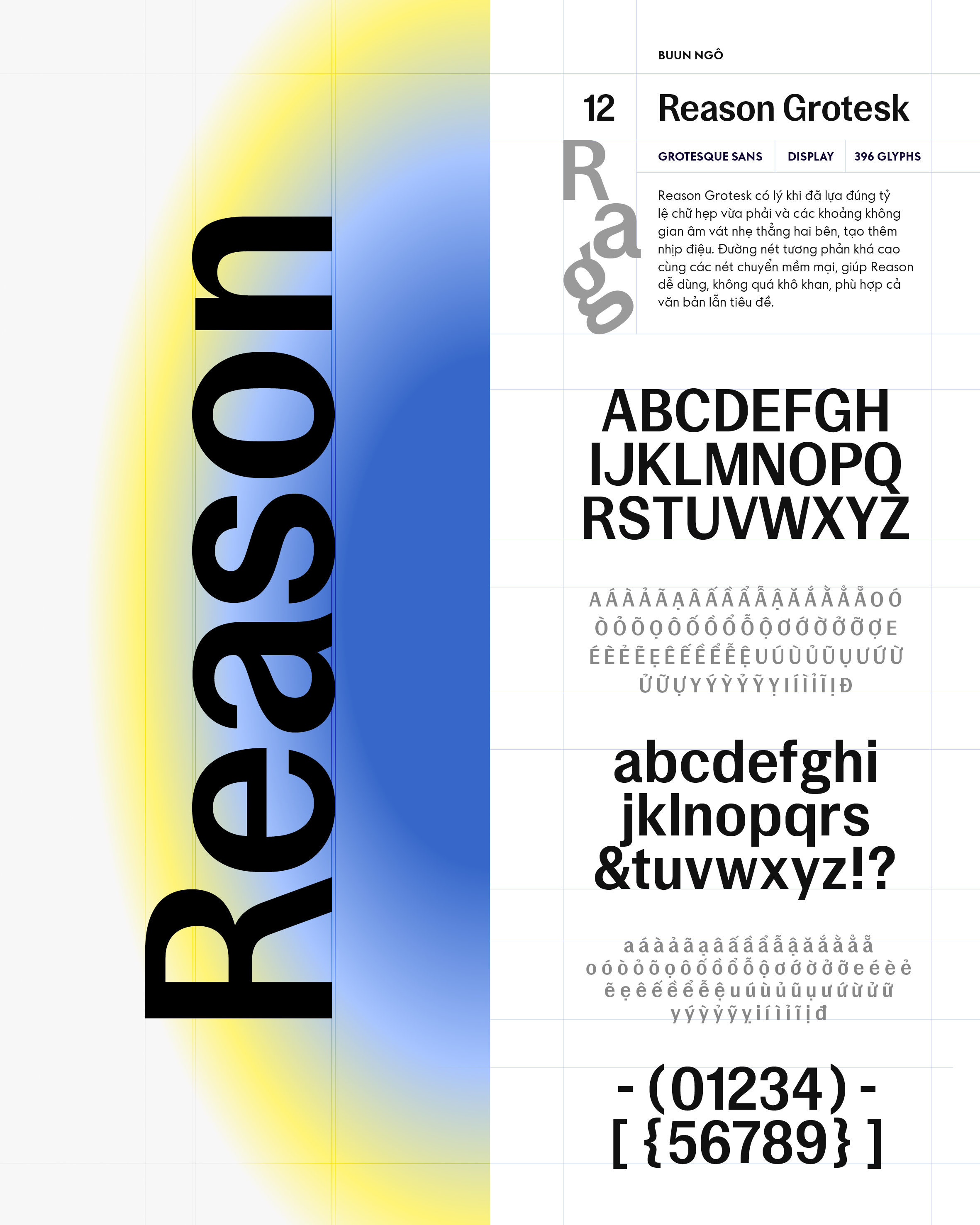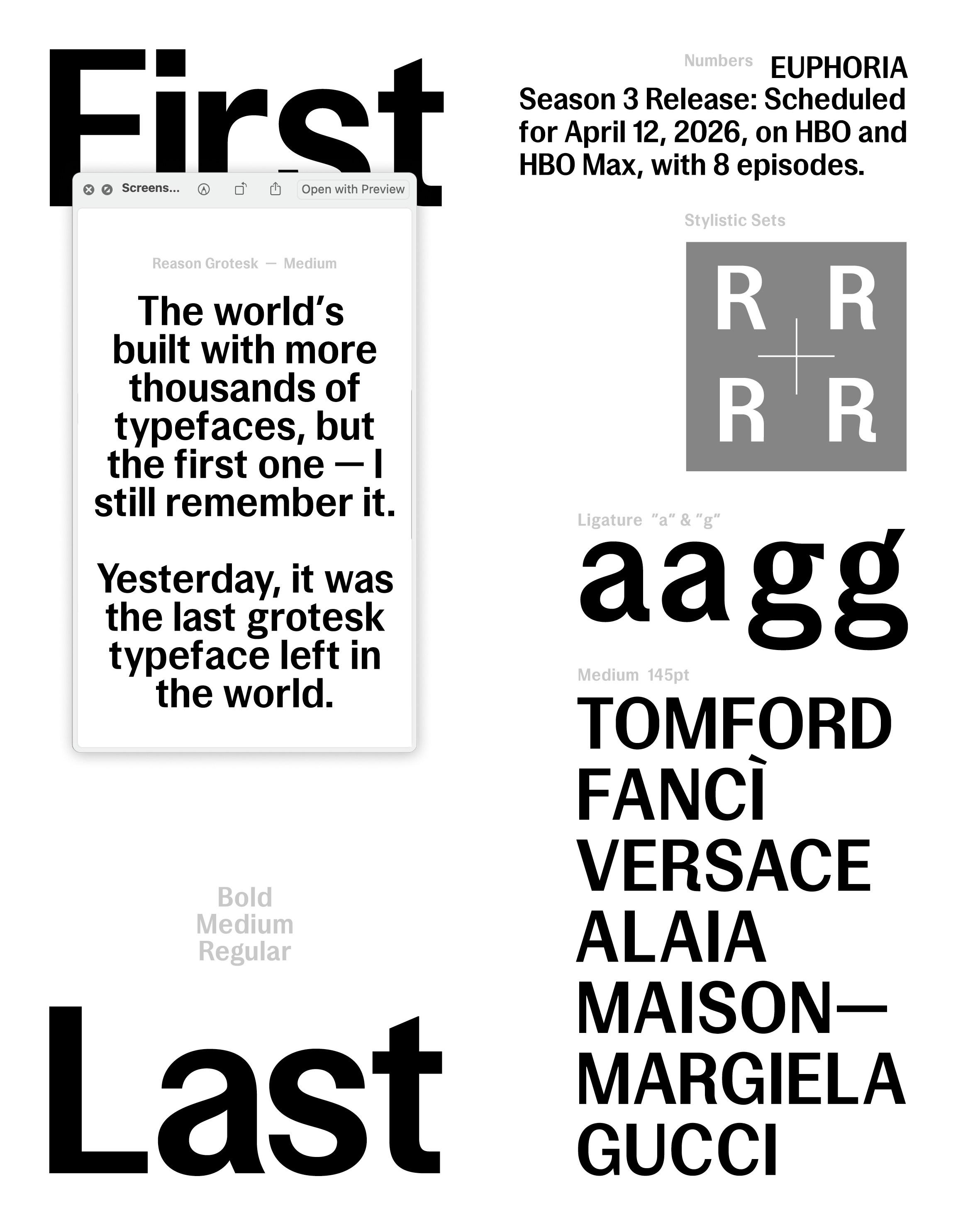
Reason Grotesk
Về Reason Grotesk: Reason Grotesk có lý khi đã lựa đúng tỷ lệ chữ hẹp vừa phải và các khoảng không gian âm vát nhẹ thẳng hai bên, tạo thêm nhịp điệu. Đường nét tương phản khá cao cùng các nét chuyển mềm mại, giúp Reason dễ dùng, không quá khô khan, phù hợp cả văn bản lẫn tiêu đề.
Grotesk Sans-serif
Buun Ngô